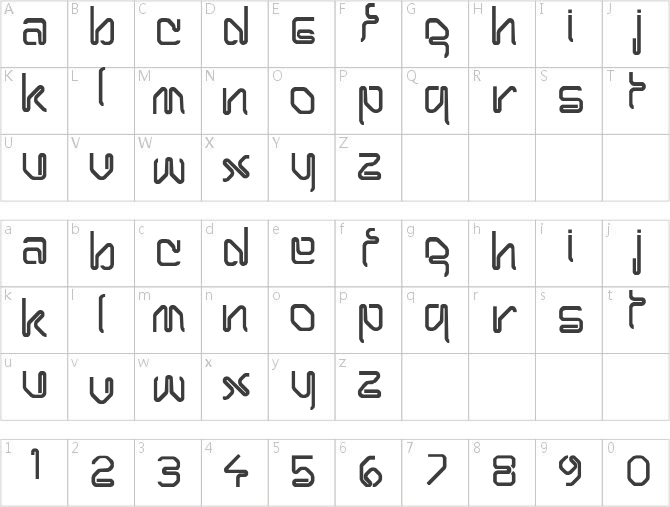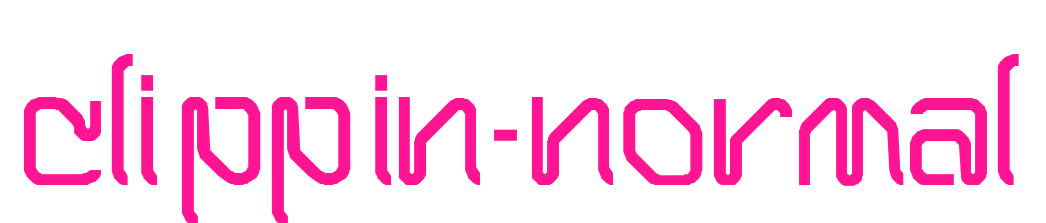
Clippin-Normal 詳情頁
字體名稱: Clippin
Clippin-Normal
Clippin-Normal介紹
Clippin-Normal字體字庫是一款讓人賞心悅目、百看不厭的英文字體,適合各類廣告和產品包裝設計應用,字體大小0.03MB,格式為ttf字體,上傳用戶是13226568769,作者/版權方為未知
Clippin-Normal效果圖